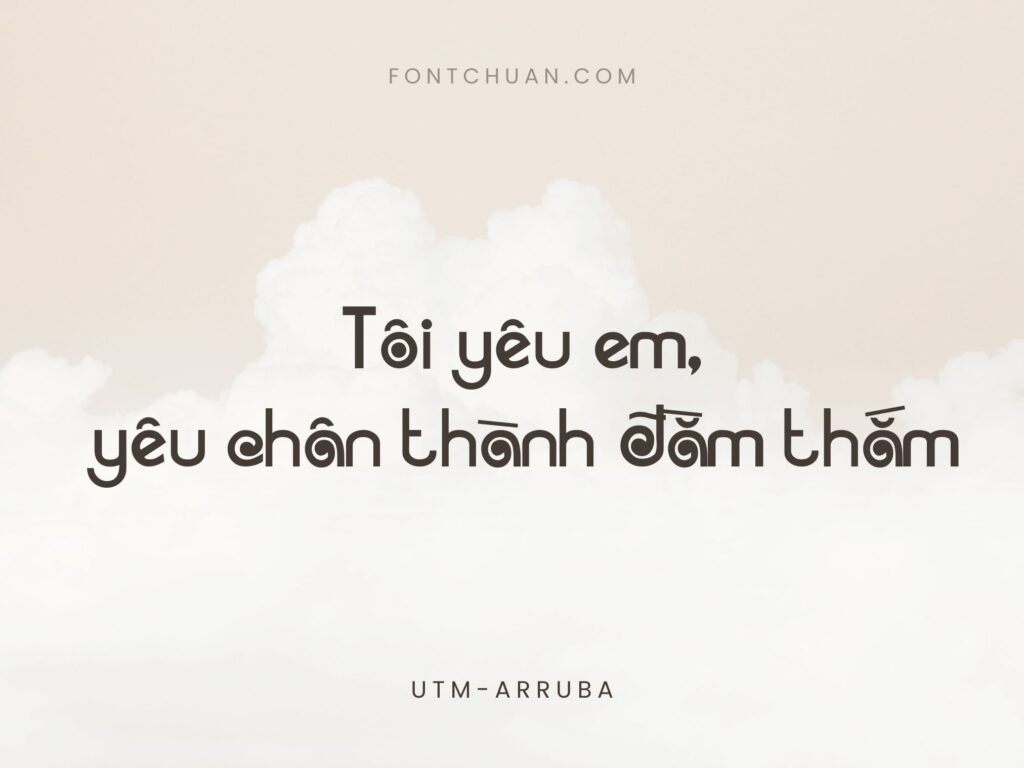
Font UTM Arruba Kt Việt Hóa
UTM Arruba là một kiểu chữ trang trí độc đáo, mang phong cách vui nhộn, sáng tạo và pha nét cổ điển của Font Vintage. Font này đã được Việt hóa bởi Đinh Kiên, hỗ trợ đầy đủ tiếng Việt cùng hơn 100 ngôn ngữ khác. Thành viên của Font Chuẩn đã sưu tầm và chọn lọc font này nhằm đáp ứng nhu cầu đa dạng của bạn đọc và ứng dụng thực tế vào các dự án thiết kế.
UTM Arruba có cấu trúc chữ với các nét cong và hình dạng đặc biệt, tạo nên sự nổi bật và thu hút. Font này phù hợp cho các ứng dụng như thiết kế tiêu đề, poster, bao bì sản phẩm và các ấn phẩm in ấn yêu cầu sự phá cách và ấn tượng. Các ngành nghề như quảng cáo, giáo dục, công nghệ và ẩm thực có thể tận dụng UTM Arruba để tạo điểm nhấn sáng tạo trong thiết kế.